UDフォントとは
UDフォント(ユニバーサルデザインフォント)とは、多くの人に分かりやすく、読みやすいように工夫されたフォントになります。
私たちは日々の暮らしの中で、印刷物、看板や標識、パソコンやスマホなどのディスプレイなど、あらゆるところで「文字」を読み、情報を取得しているため、文字は大変重要な役割をもっています。
近年では高齢化にともなって、細かな文字や小さい文字が読みにくいといった人が増えていることや、社会全体がより多くの人にとって暮らしやすいユニバーサルな社会を目ざしていることから、UDフォントの重要性は高まっています。
UDフォントと一般フォントの比較
例えば、数字の「6」と「8」の文字ですが、アキの部分が狭いと見間違いを起こしやすくなります。そのような問題を解消するために、UDフォントではアキの間隔や、文字の幅などを調整して判別しやすくするといった工夫が取られています。
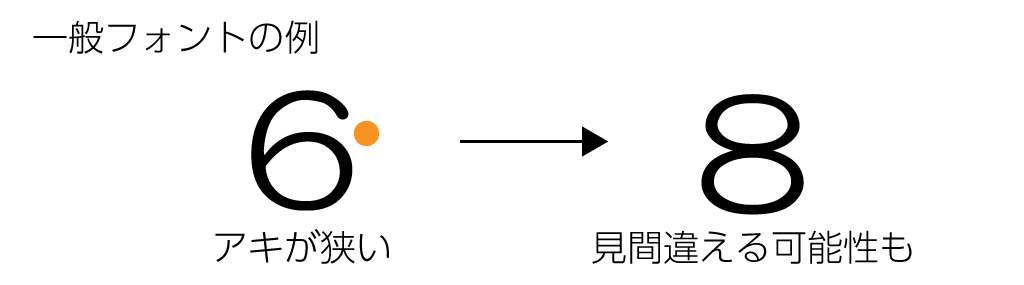
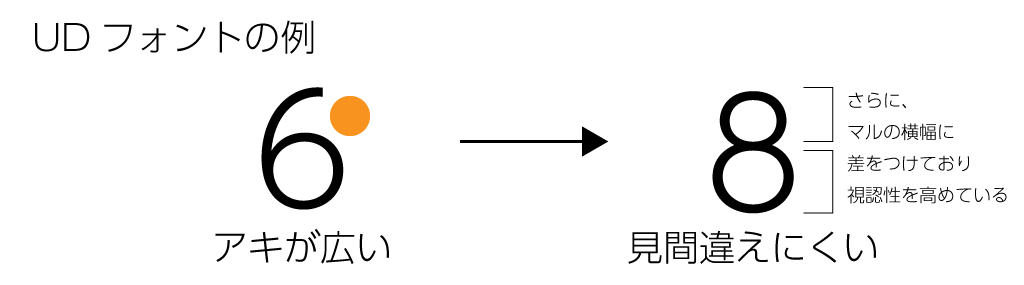
見間違い以外にも、
・コピー機でコピーを取る
・FAX送信をする
このような場面では文字がつぶれやすくなるため、やはり見分けがつきにくくなる場合があります。いくら視力が良くても、文字がつぶれてしまっていては正確に判別することはできませんね。UDフォントはこのような場面も想定して、なるべく読みやすく、分かりやすいデザイン設計がなされています。
暮らしの中で見かけるUDフォントの事例
より暮らしやすい社会のために、UDフォントは日常のあらゆるところで使われています。
例えば、町の広報誌や掲示物、駅名の看板、医療や福祉の現場で使われる印刷物など様々です。最近では、東京オリンピック・パラリンピックの公式フォントとして、フォントメーカーのモリサワが「東京2020公式フォント」をデザインし、提供するといったニュースが話題になりました。
もちろん、UDフォントを使っているだけではなく、読みやすく分かりやすいレイアウトや文字組み、色使いなども重要です。多くの人に伝わる、思いやりのあるデザインを広めていきたいですね。